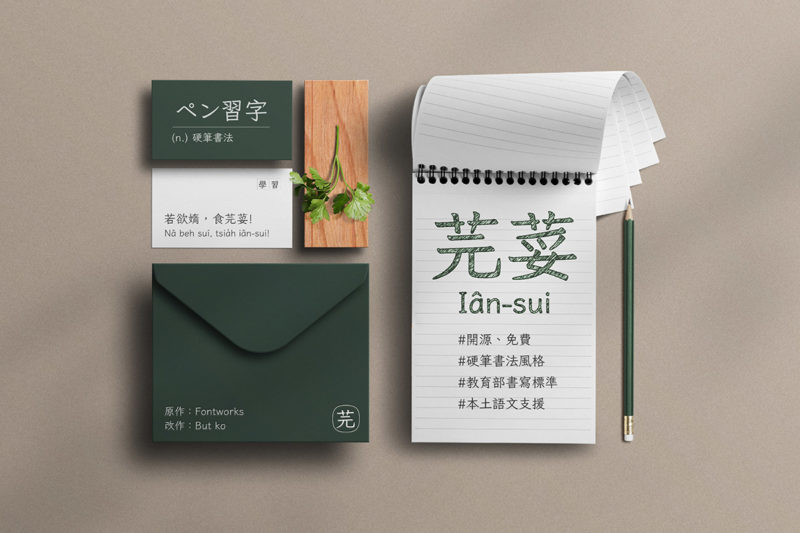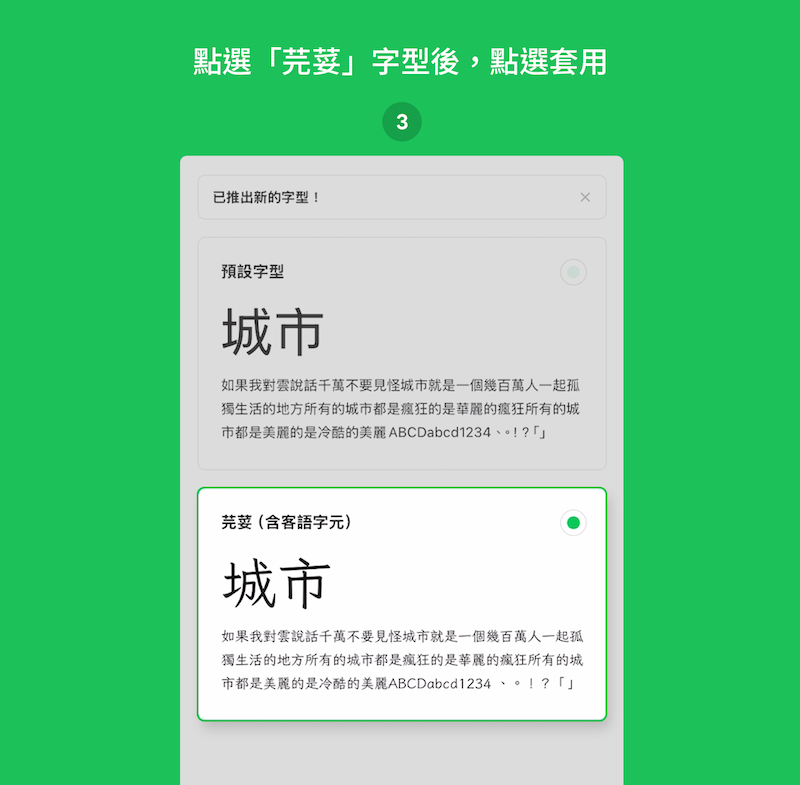
LINE 內建「芫荽」字型、3 步驟輕鬆套用,台客語不缺字
更新 LINE 行動版後,App 內建免費「芫荽」字型提供使用者選用,讓 App 介面展露新貌。
開源字型「芫荽」(ㄩㄢˊ ㄙㄨㄟ,俗稱香菜)的誕生,是為提升繁體中文在數位環境的使用體驗,補充台灣本土語言用字(如客語漢字、台語漢字、原住民族語羅馬字等),讓言詞使用更到位。
現在 LINE 行動版能夠套用「芫荽」,不只對話內容,包括帳號名稱、功能選項等換不同字型,使用上比預設字型有不同感受,也讓台客語用字不缺字,至於 LINE 提供的服務如貼圖小舖、LINE 購物等維持原貌。
「芫荽」字型如何誕生?
「芫荽」字型是以日本字體公司 Fontworks 的 Klee(クレー)字型為基礎,由「字嗨」社群發起人 But Ko 改作而成的開源繁體中文字型,提供使用者自行下載套用,甚至允許商業用途。
GitHub 上的「芫荽」專案簡介指出,Klee 原本內建於 macOS,因其兼具楷體筆調、又似仿宋整齊端正,具高易讀性與溫暖外形,廣受中文使用者喜好。不過,Klee 畢竟是日文字型,雖然字數不少,但排中文仍有一定程度缺字。2020 年底,Fontworks 開源釋出 Klee One 字型,震驚字型圈,網路上也有其他專案嘗試為 Klee One 補上中文字。
「芫荽」專案盡可能調整字形以貼近教育部標準字體,並補充台客語用字,不僅貼近台灣人需求,可提供學齡教育使用(如童書、國字習作等)。